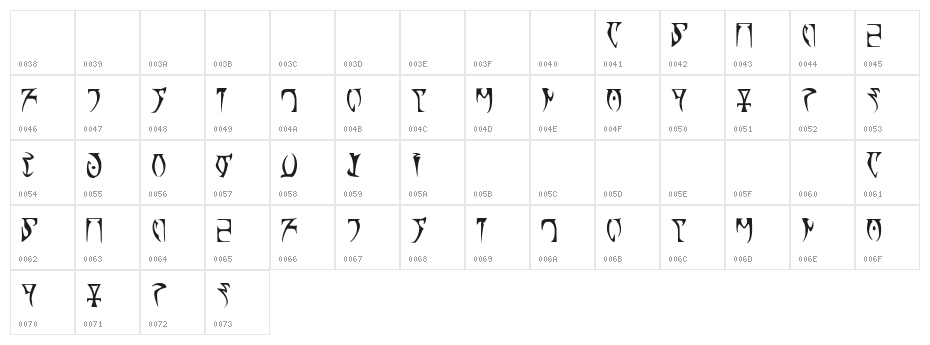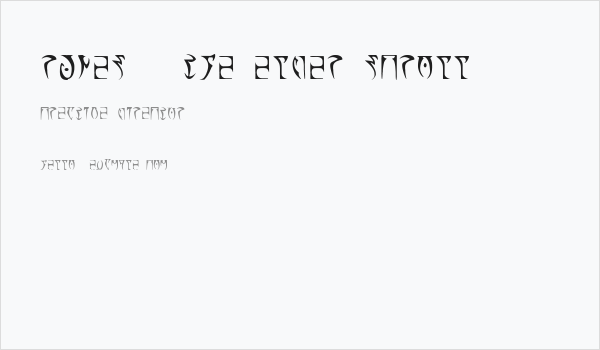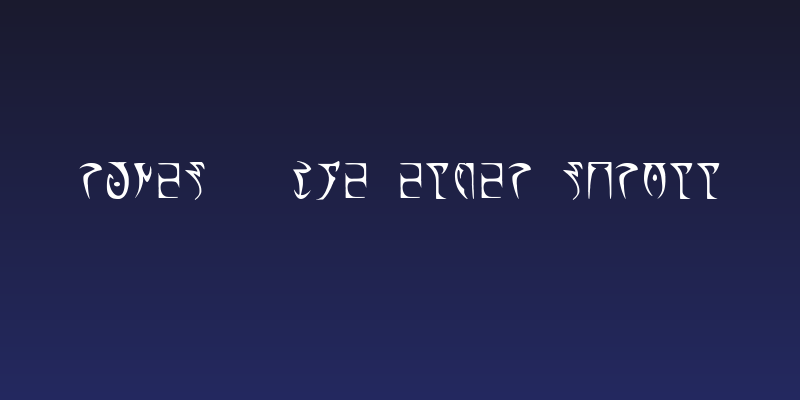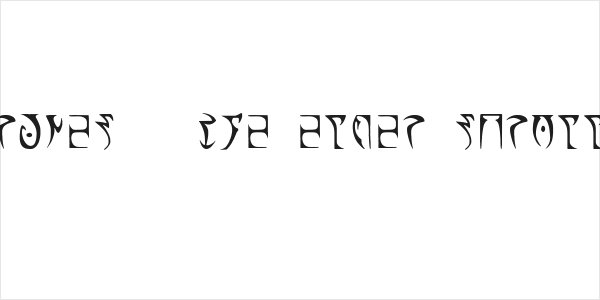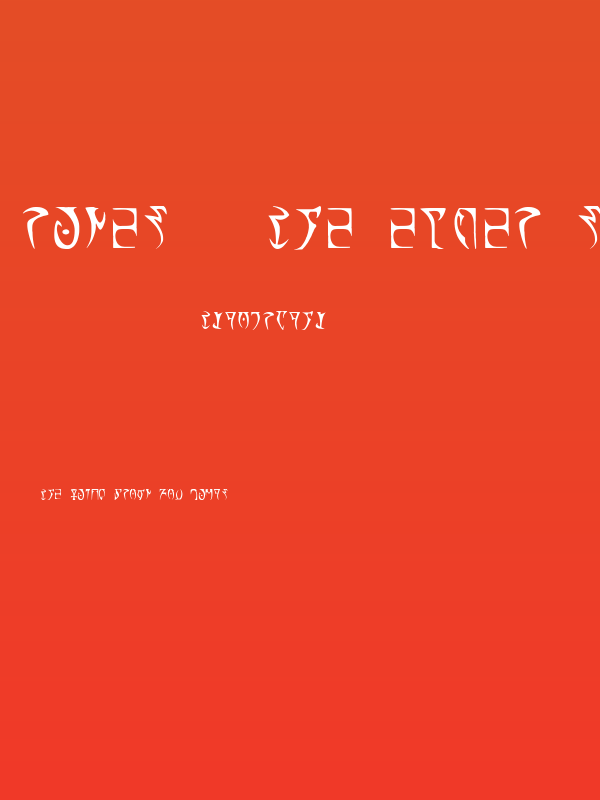
Runes - The elder scroll Font
| 整体风格 | Mystical, Ancient, Fantasy |
| 使用场景 | Logos, Headlines, Themed Designs |
| 推荐项目 | Ideal for fantasy book covers, game design, movie posters, and themed event invitations. |